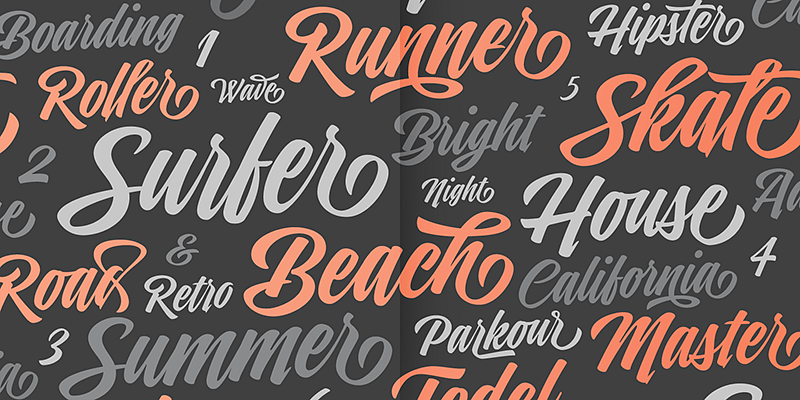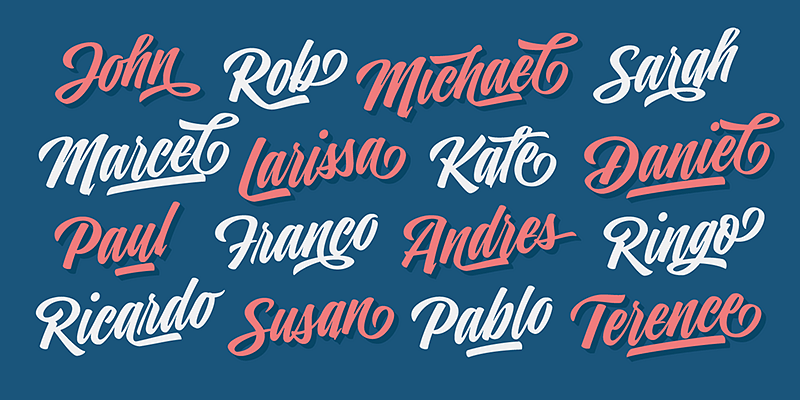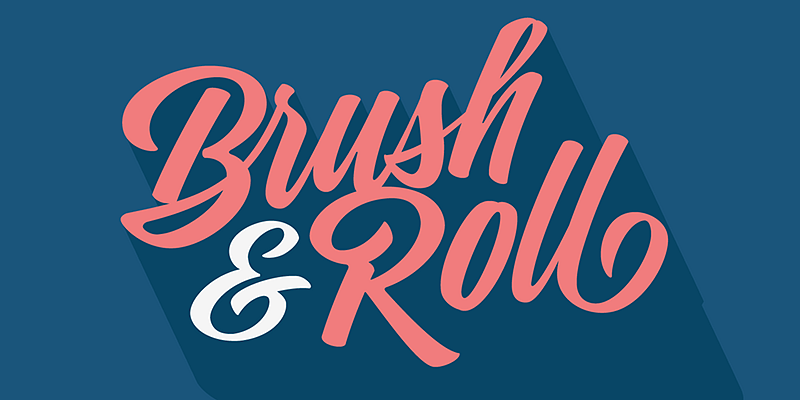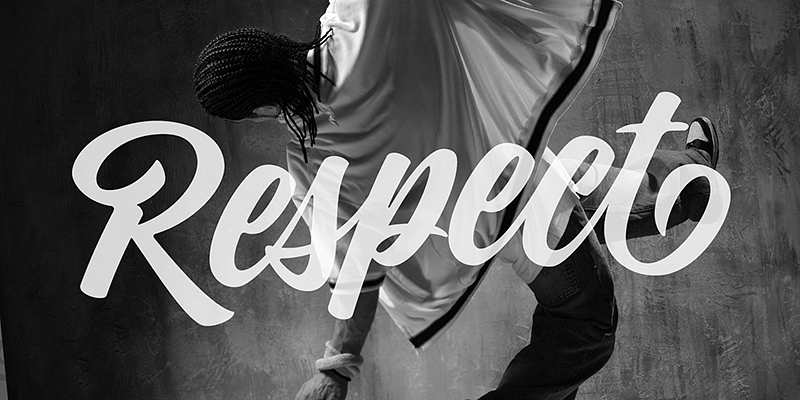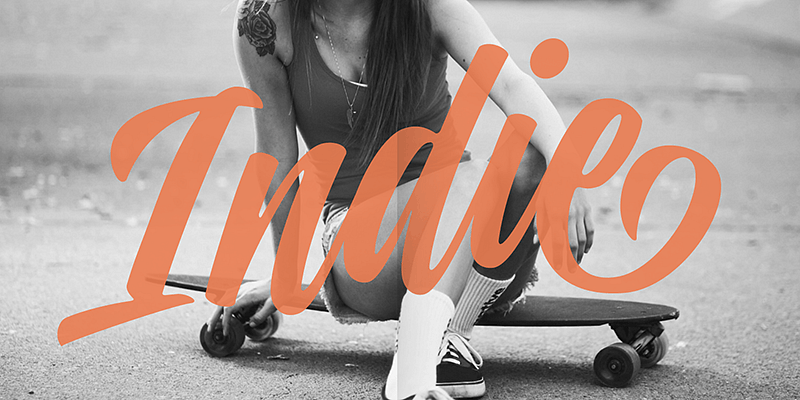
Sproviero Type は、細部まで手を抜かずに、複雑で美しくモダンな書体の受賞歴のあるカタログを作成しました。書体デザイナーの Maximiliano Sproviero は、カリグラフィーとレタリングに対する情熱を、幻想的に装飾され、想像力豊かに表現され、息を呑むほど独創的な個々の書体の印象的なコレクションに注ぎ込みました。製品やメディアが何であれ、Sproviero Type のフォントは、自身の考えやアイデアを現実に変えるための準備を整えるのに役立ちます。